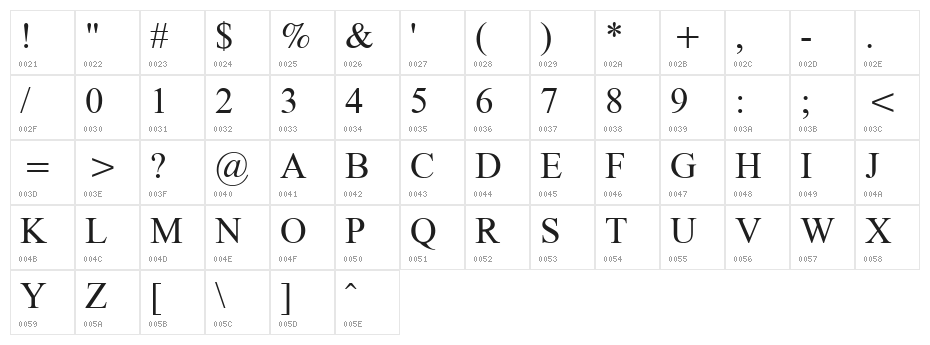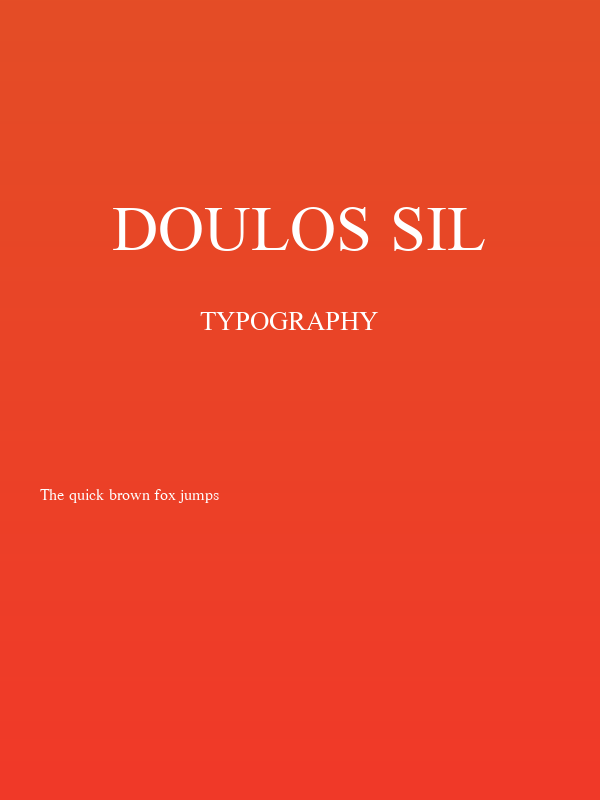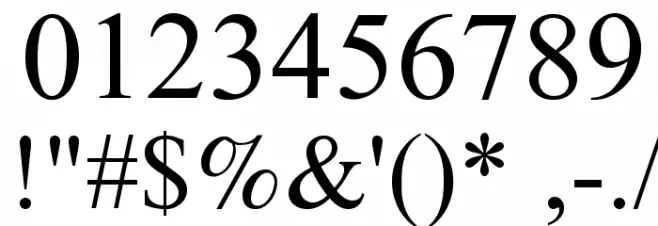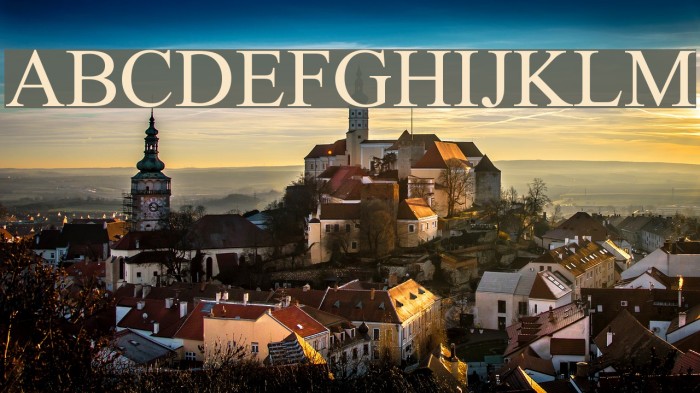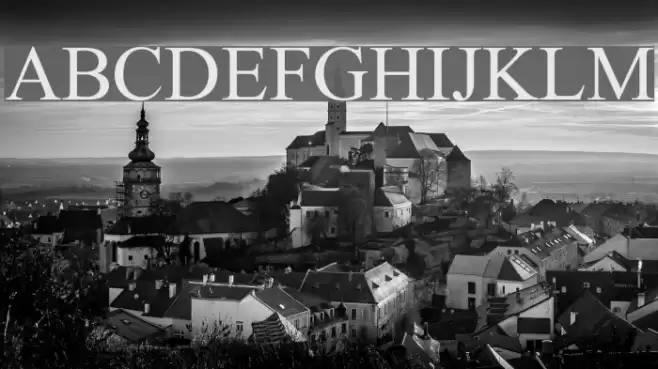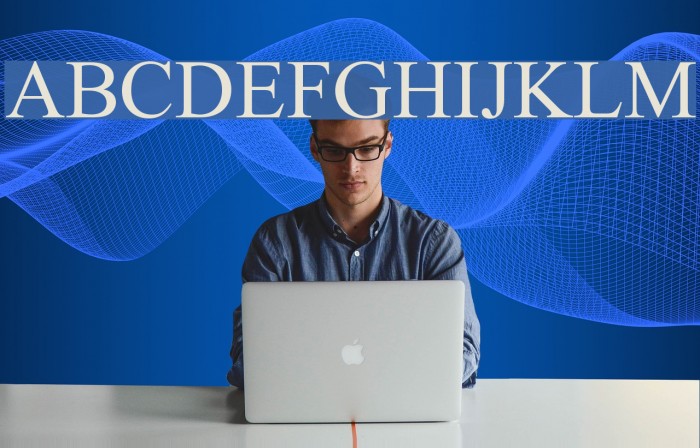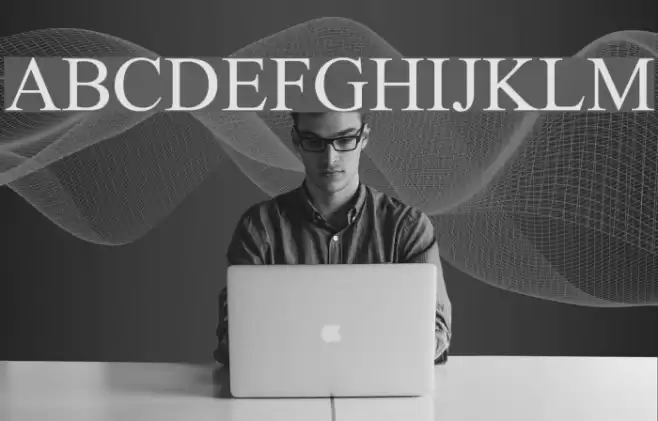
Doulos SIL Font
| Nome | Doulos SIL |
| Caso de uso | Body text, Headlines, Formal documents |
| Projetos propostos | This font is perfect for projects that require a touch of elegance and tradition, such as book typesetting, formal invitations, academic publications, and sophisticated branding. |